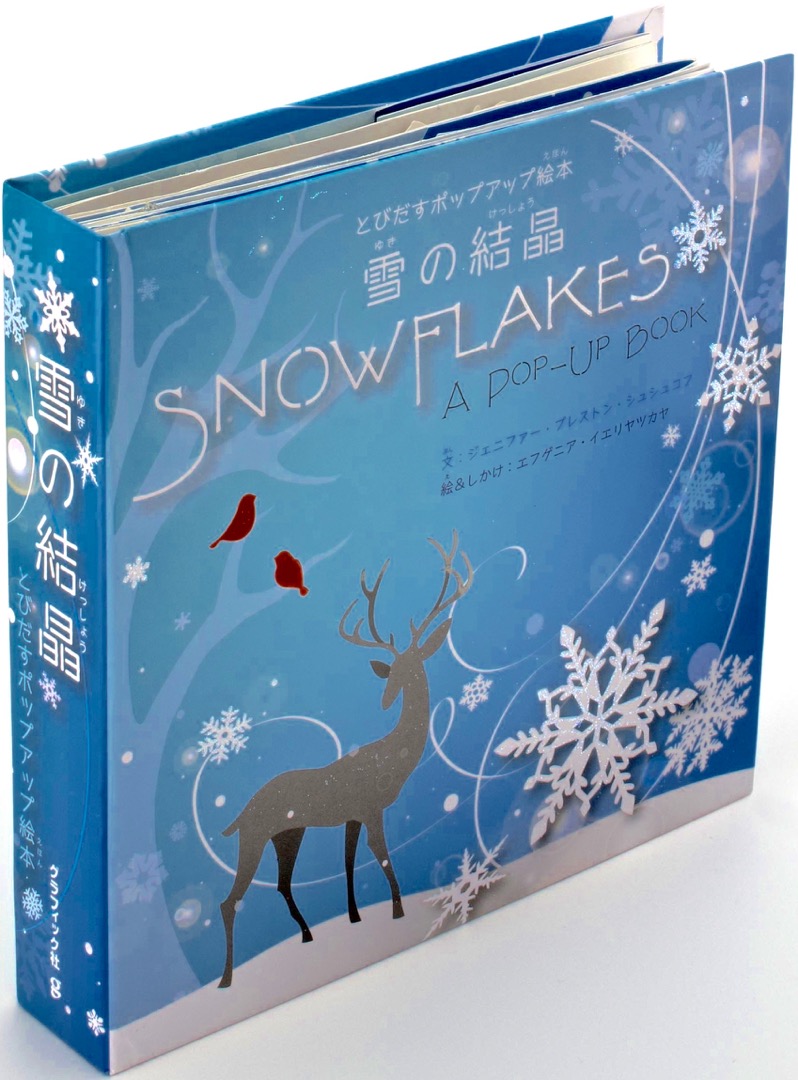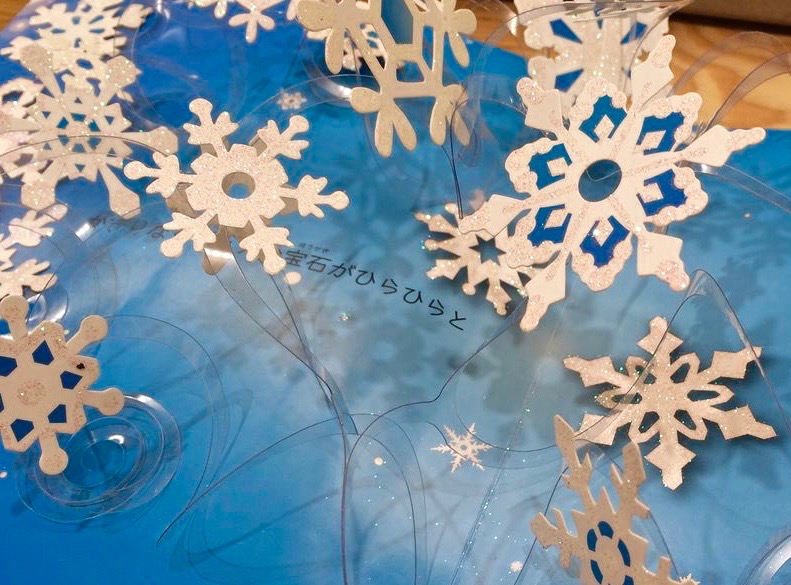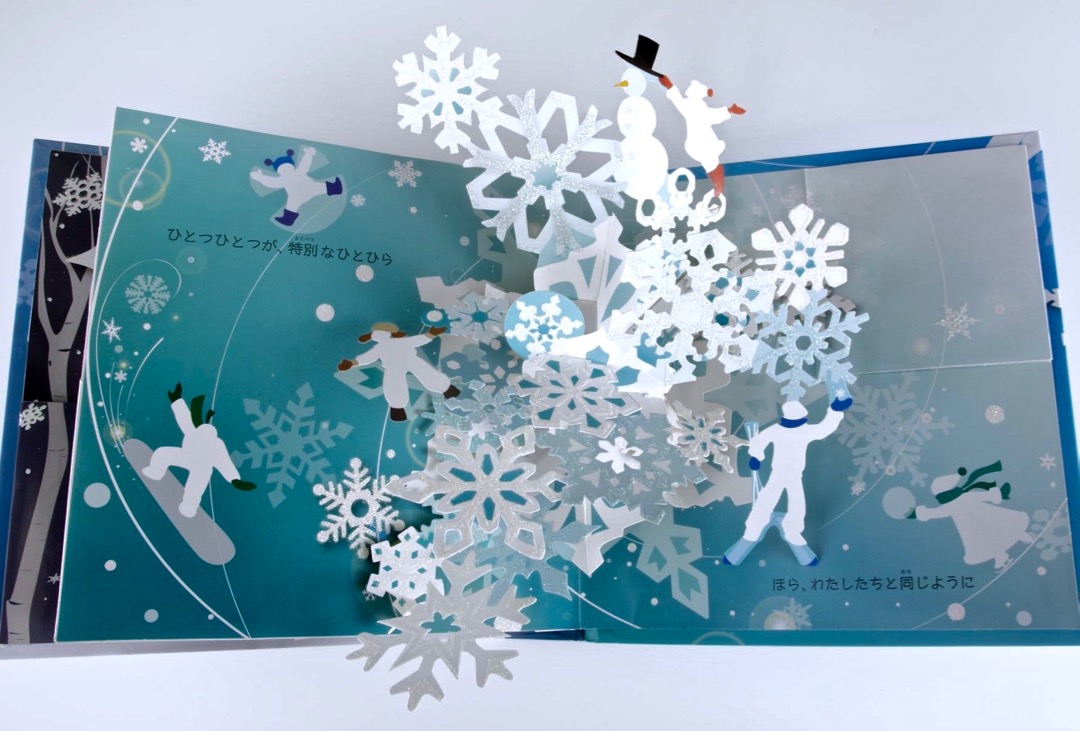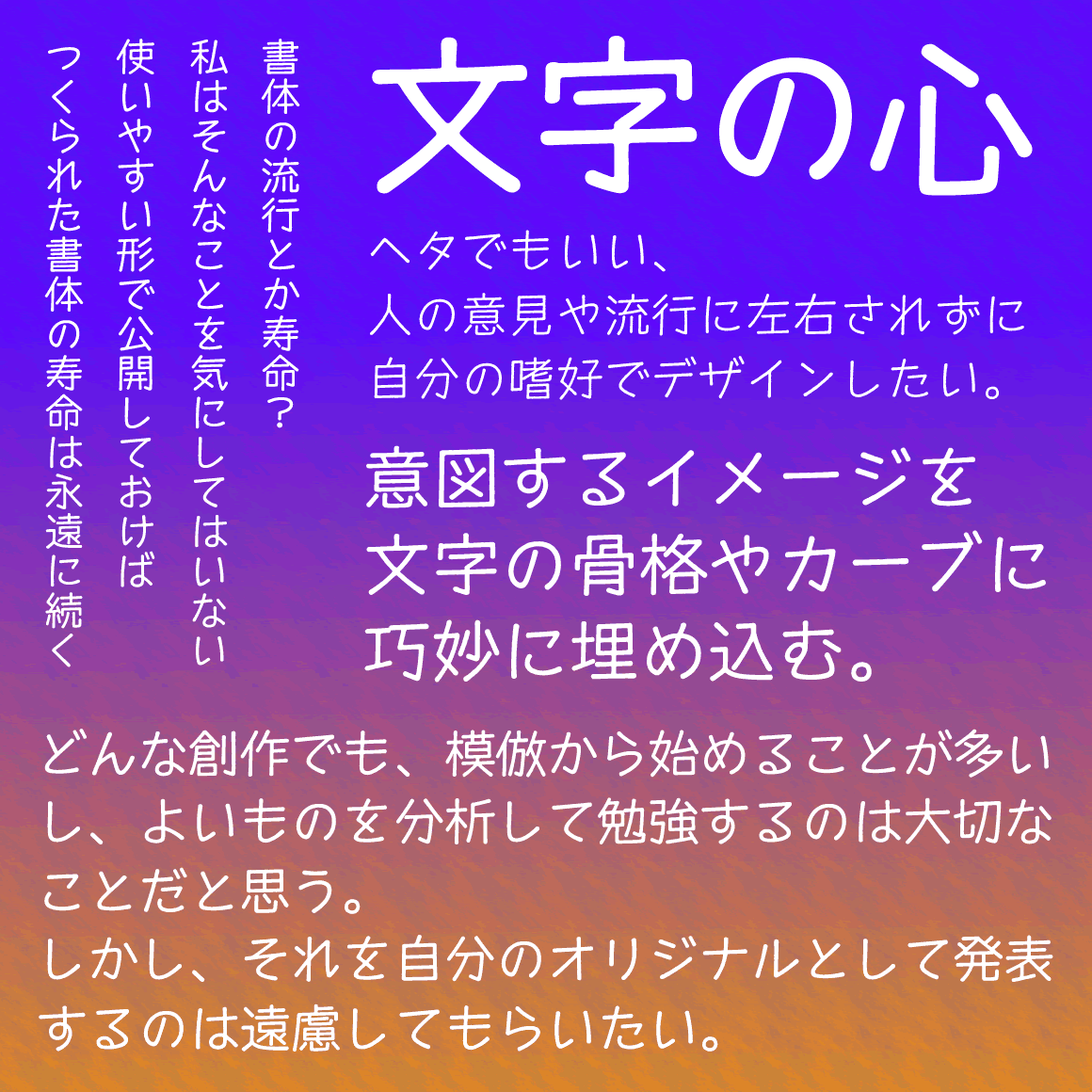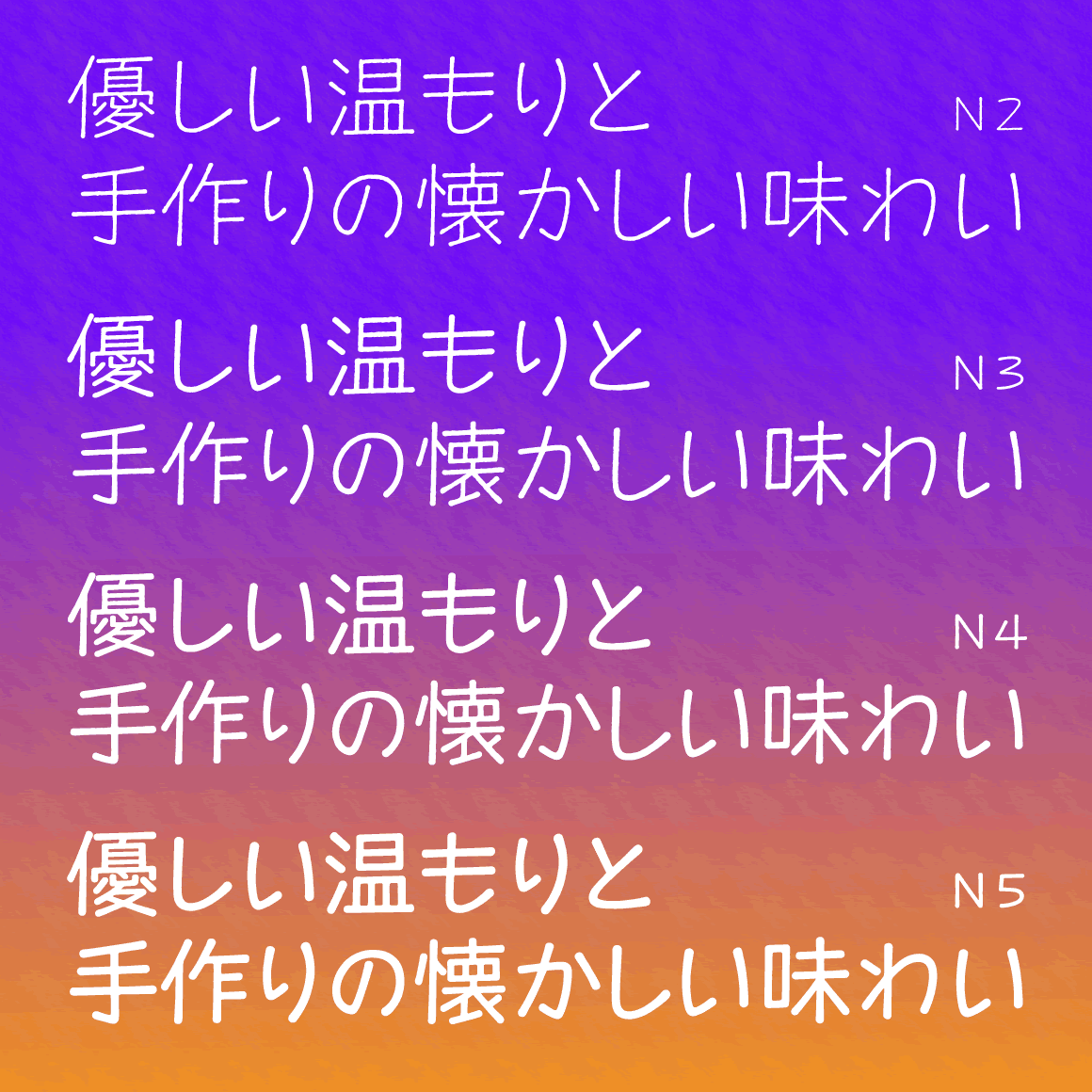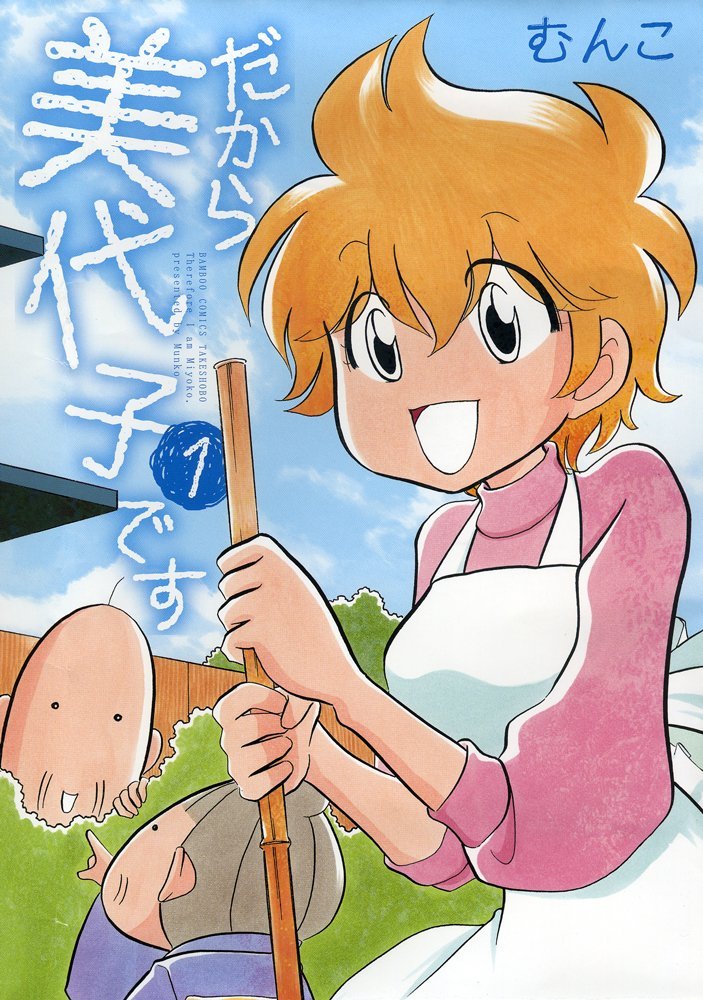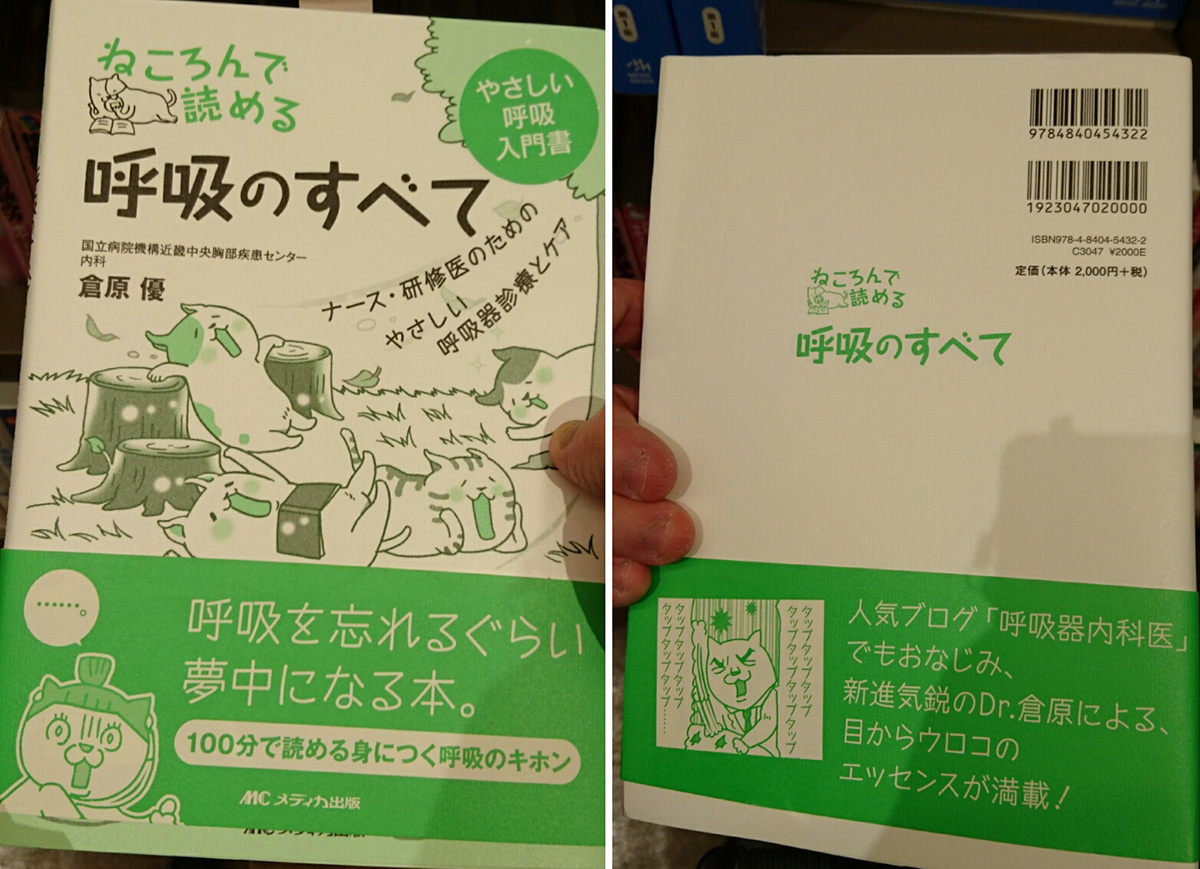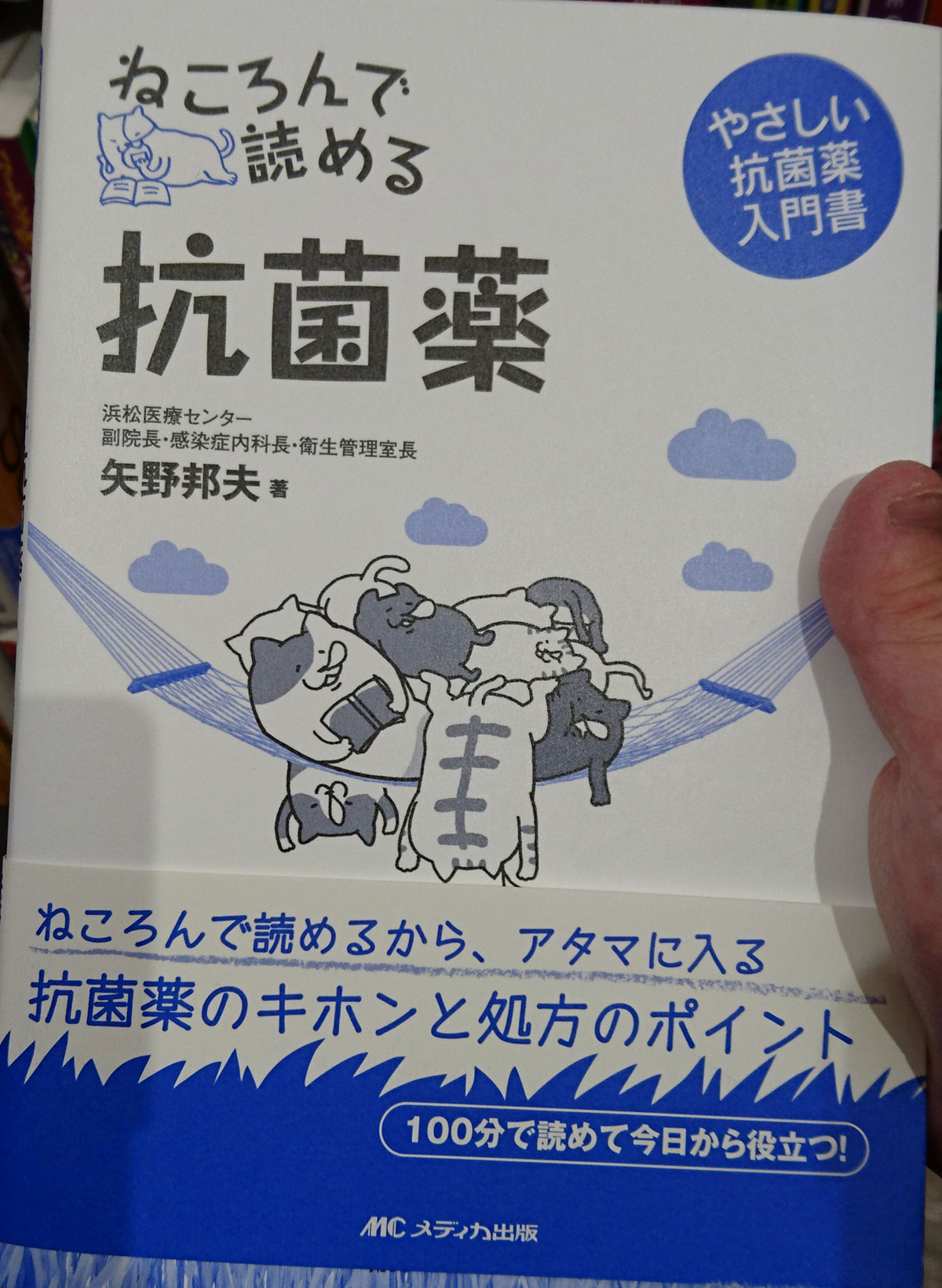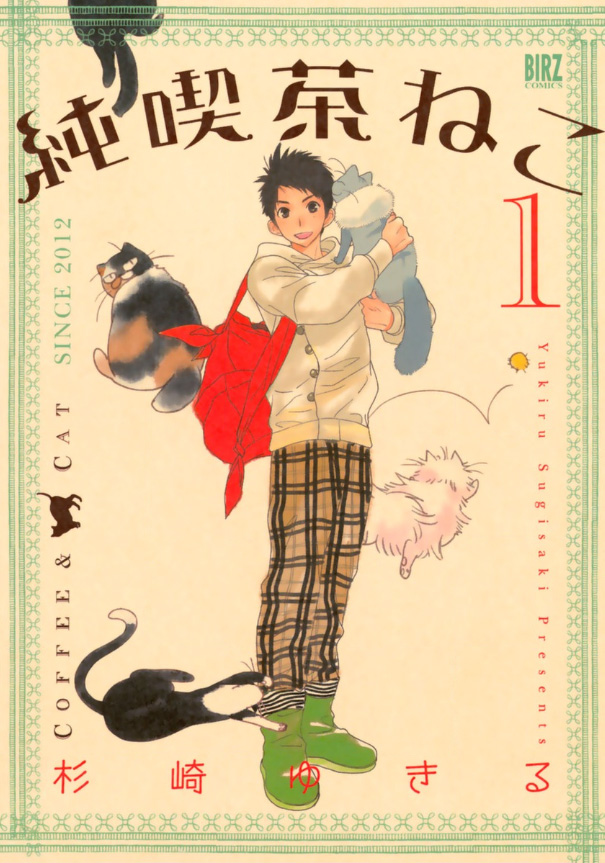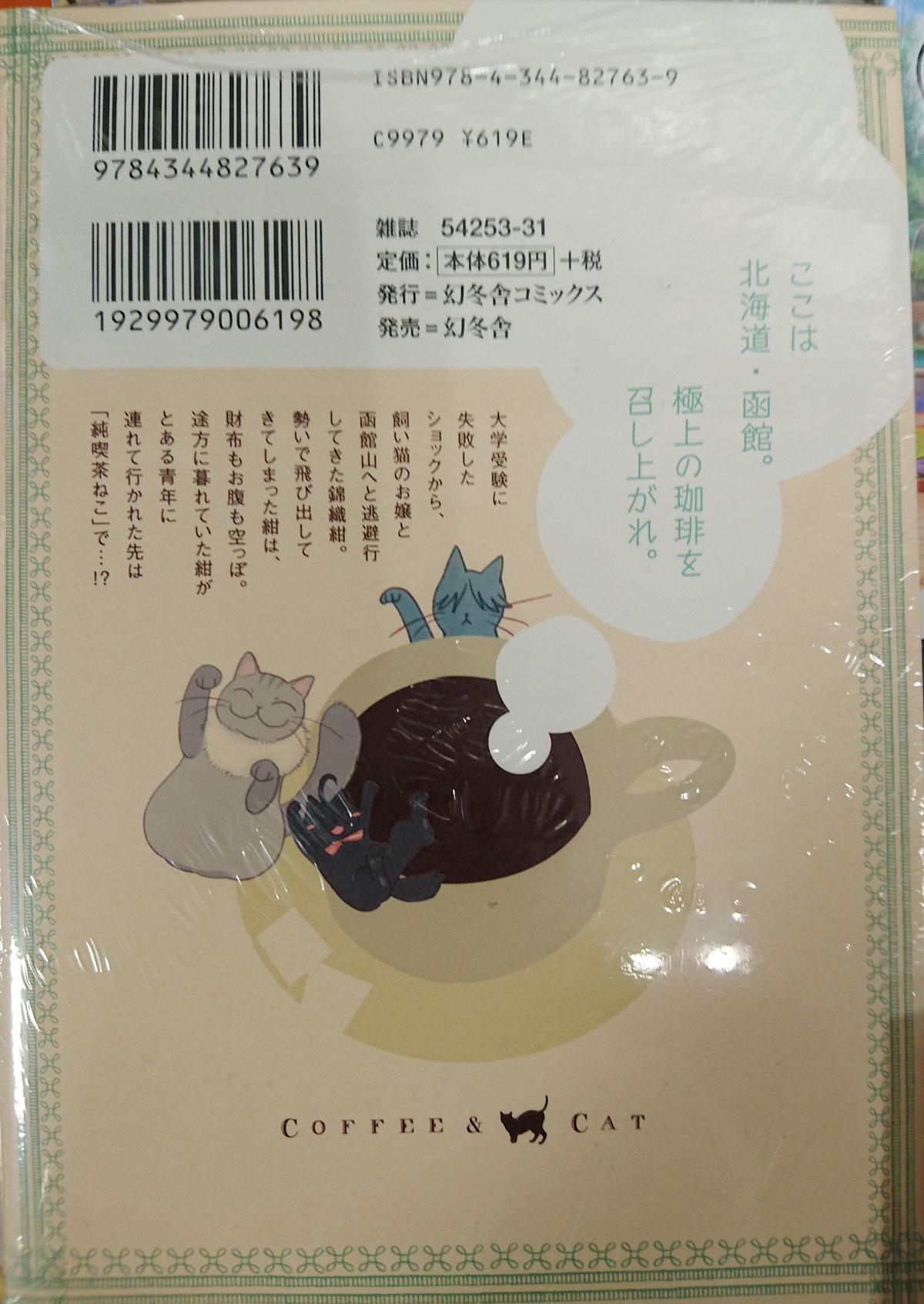
団体ロゴ  さとうゆたか  2019年6月19日(水) 7:41
絵本セラピスト協会。
発表会の資料  さとうゆたか  2019年6月2日(日) 8:39
第138回 PHP勉強会@東京で発表された資料。
ここで配布されているPDFには、セプテンバー書体がたっぷり使われています。
本の表紙  さとうゆたか  2019年5月28日(火) 15:58
書名:ナタンと呼んで
著者:カトリーヌ・カストロ、カンタン・ズゥティオン
発行:花伝社
「演歌歌謡通信」見出し  大阪のうめ吉  2018年11月24日(土) 18:03  Mail
制作中のミニコミ紙「演歌歌謡通信」の見出し&リードです。
縦組みのセプテンバー、いいですね。
WEBフォントで  さとうゆたか  2018年5月10日(木) 13:41
こちらのサイト「本棚散歩」で、WEBフォントとして使われている。
スマホから見ると、こんな感じ。
ドーナッツのお店の看板で  takumi  2018年5月2日(水) 22:11  HP
今日、出先で「はらドーナッツ」というお店の前を通りかかった時に、そこの看板(メニュー)でセプテンバーが使われているのを発見しました。
これまでよくあった太らせたものでなく、2016年に新しくなったセプテンバーN…のような気がしましたが、いかがでしょうか。
Webサイトでも  takumi  2018年5月2日(水) 22:16  HP [修正]
サイトに配置されている画像でも、セプテンバーを使っているようです。
ここまできたら、ぜひともFontStreamで使えるセプテンバーNのWebフォントも採用して欲しいなぁ、なんて(笑)。
セプテンバーNかどうか、ちょっと判断できないですね…。
このドーナツ屋さんの使用例は、2015年5月に掲載したことありますが、新しい使用例はありがたいです。
ミニコミ紙で使用  大阪のうめ吉  2018年4月30日(月) 9:03  Mail
作っているミニコミ紙「演歌歌謡通信」で使わせてもらいます。見出しに使っています。制作中のこの号(5月2日発行)のトップ記事です。
半世紀をはるかに超える新聞づくりで、なつかしさを感じるフォントです。新聞づくりの最初はガリ版でしたから。
大手フォントベンダーから販売されていないので、この書体の使用例は少ないのです。
本の表紙  さとうゆたか  2017年11月30日(木) 21:37
書名:校閲記者の目
著者:毎日新聞・校閲グループ
発行:毎日新聞出版
セプテンバーN、
ちょっと手書き風味であったかい、ほのぼの路線だけどバランス良い…って感じがします。
セプテンバーのフリーフォント、可愛くて素直な感じで
でも甘すぎない、子どもっぽすぎないところが大好きで
これまでもプライベートで愛用させていただいておりました。
(わたしの名刺はここ数年ずっとこちらの書体です)
セプテンバー,堅すぎず緩すぎずで重宝しそうです。
フリーフォントや格安フォントではウェイトがそろっているものが少ないので,重宝しそうです。
シンプルでかわいいフォント大切に使わせていただきます。
「セプテンバーL」は初めて買ったフォントで、Windows組み込み以外のフォントに目を向けるきっかけとなった物です。
今回若干太めの「N4」を頂戴しました。
文書の全体感を見たくて早速、以前作成していた文書で確認してみました。
やっぱりかわいい!かたすぎずゆるすぎずで、親しみやすい感じが好きです。
佐藤さんのサイトを拝見して、一つのフォントの作成に多大なエネルギーを注がれることを知りました。フォントや、デザインに対する見方がずいぶん変わりました。大切に使わせていただきたいと思います。
程よいくだけ具合が使い勝手よさそうです。
セプテンバーNフォント、早速使ってみました。
とても温かみがあってやさしいイメージのフォントですね。
ほっこり柔らかく、それでいてすっきり読みやすくおしゃれなので子供向けのチラシ、フライヤーにピッタリだと思いました。これからどんどん活躍してくれそうです。
(クラウディアジャンセン)薬用ハンドソープ  ミニヘイ  2017年9月27日(水) 20:44  HP
ドラッグストアでセプテンバーフォントが使用されているハンドソープをみつけました。もう1つピンク色のものもあり(本体ボトルはみかけませんでした)。セプテンバーN2を少しふとらせているのでしょうか ٩( 'ω' )و